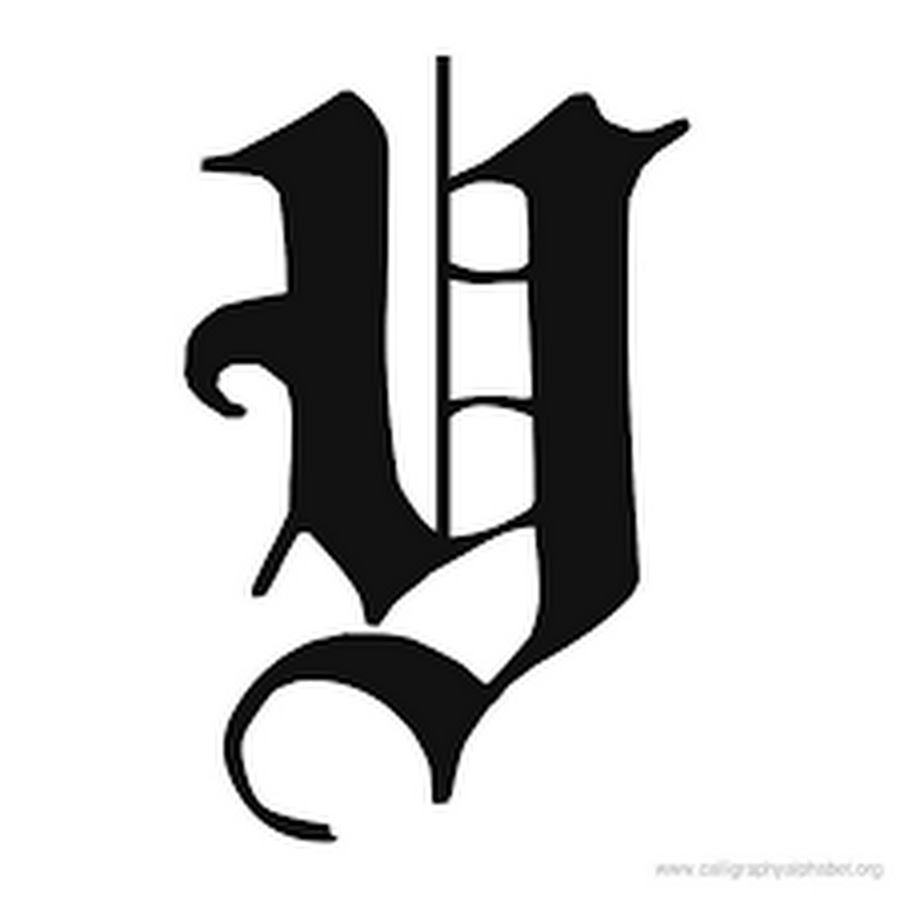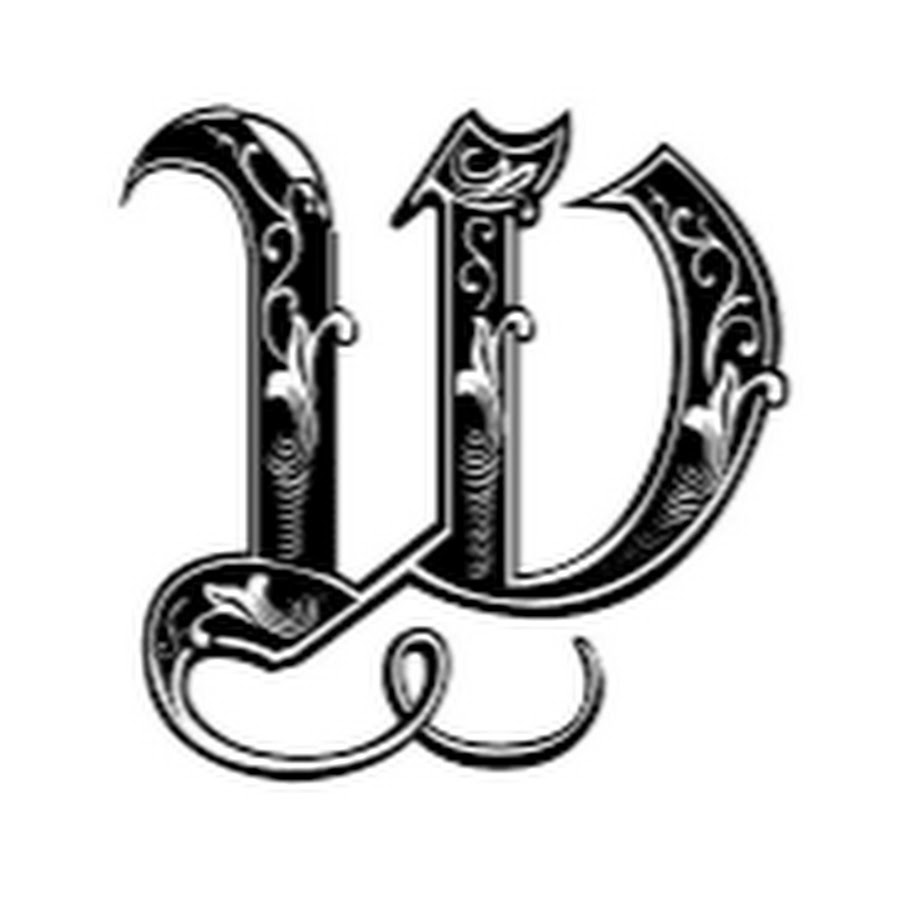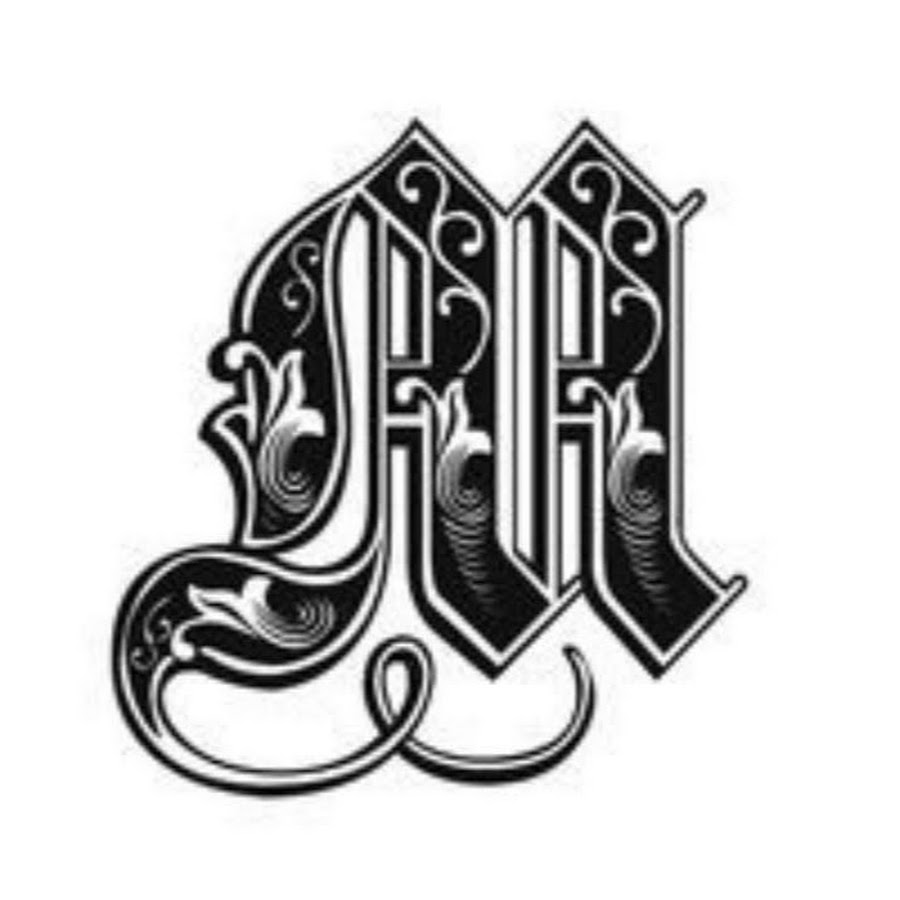
буквы, представляющие своим очертанием подражание вычурному почерку средневековых времен.
готические шрифты — (Blackletter, Broken script) Собирательное название наборных шрифтов, по рисунку имитирующих средневековые рукописные почерки ширококонечным пером, распространенные в XIII XVI веках главным образом в северной Европе.
Первая серия уроков раскроет секреты создания каждой буквы латинского алфавита, а также каждой цифры. Вторая — о процессе создания каллиграфических надписей, композиции и разнообразии инструментов, которые применими для создания готической каллиграфии.
Написание готического алфавита
Hamid Reza Ebrahimi в течение последних нескольких недель выкладывал видео-уроки по написанию готической каллиграфии.
Создание готической каллиграфической надписи
От готического письма к гравировальным отделкам
Важный пласт современной типоакциденции связан с готическим письмом. Как известно, готическая каллиграфия, в значительной степени укорененная на церковной почве, перевоплотилась в наборные шрифты, которые начали свою жизнь со знаменитых библейских проектов первопечатника Гутенберга. Минули века, и готические шрифты перестали использоваться в наборе периодических изданий и книг. Однако шрифтовые стилизации на готические темы продолжают свою жизнь в акциденции: от престижных логотипов до этикетки и упаковки, причем зачастую этой графике сопутствуют различные формы декорирования.
От готического письма к гравировальным отделкам
Что может связывать гравировальное декорирование с готической каллиграфией? С чисто формальной точки зрения вроде бы ничего.
На самом деле это, конечно же, не так, в доказательство чего рассмотрим конкретный пример.
На рис. 1 приведена оригинальная кириллическая локализация, созданная на базе шрифта Blackletter 686 фирмы Bitstream, который входит в поставляемую с пакетом CorelDRAW шрифтовую библиотеку. Примененная техника накладного гравировального декорирования ранее подробно рассматривалась почти во всех статьях данного цикла относительно к другим видам шрифтовой графики. При этом акцидентные достоинства представленного шрифта вполне очевидны.